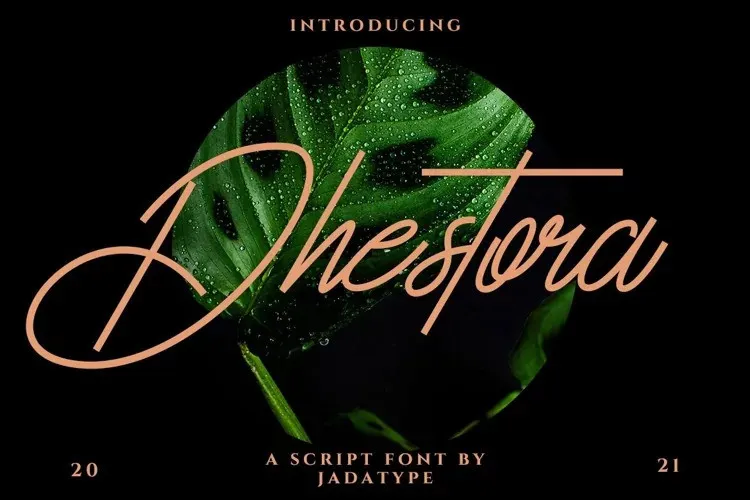
A Dhestora Font é uma elegante tipografia estilo linha única projetada para estilos sofisticados e criativos. Seu design minimalista cria um equilíbrio harmonioso entre modernidade e charme, tornando-se um recurso versátil para diversas aplicações. Ideal tanto para marcas de marca quanto para títulos de livros ou produtos exclusivos, essa fonte também oferece suporte a letras multilinguas, permitindo uma ampla gama de usos. Seja em softwares como o Adobe ou o Affinity, essa Dhestora Font é fácil de instalar e adaptar às suas necessidades, tornando-se um excelente investimento para designers e criadores de conteúdo que buscam adicionar um toque único a seus projetos.